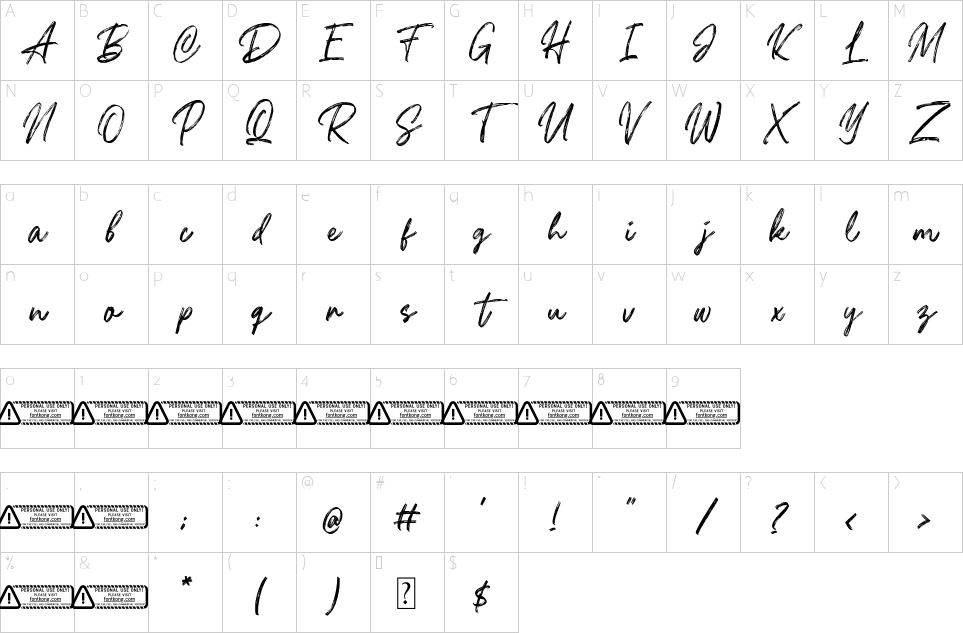
A Martabug Font é uma fonte agradavelmente leve e elegante, perfeitamente adaptável a uma ampla gama de projetos gráficos. Desenhada pelo incrível equipo da Font Kong, essa fonte possui um conjunto de caracteres amplo e uma excelente legibilidade. Ela foi projetada para complementar seu projeto e deixá-lo brilhar. A Martabug Font já foi baixada 1.254 vezes, provando a qualidade e a popularidade que ela tem. Se você está buscando uma fonte para um projeto gráfico criativo, que seja não apenas agradável de ler, mas também um charme visual, então a Martabug Font é perfeita para você. Descubra por si mesmo o poder da Martabug Font.